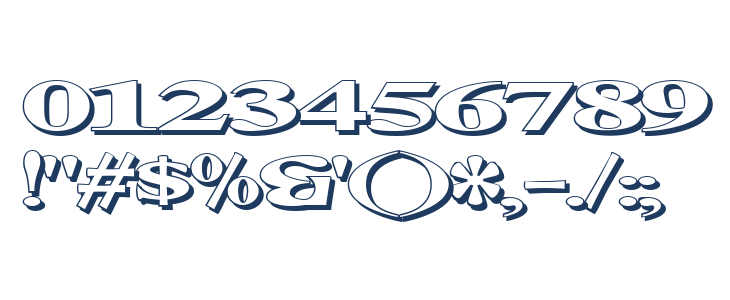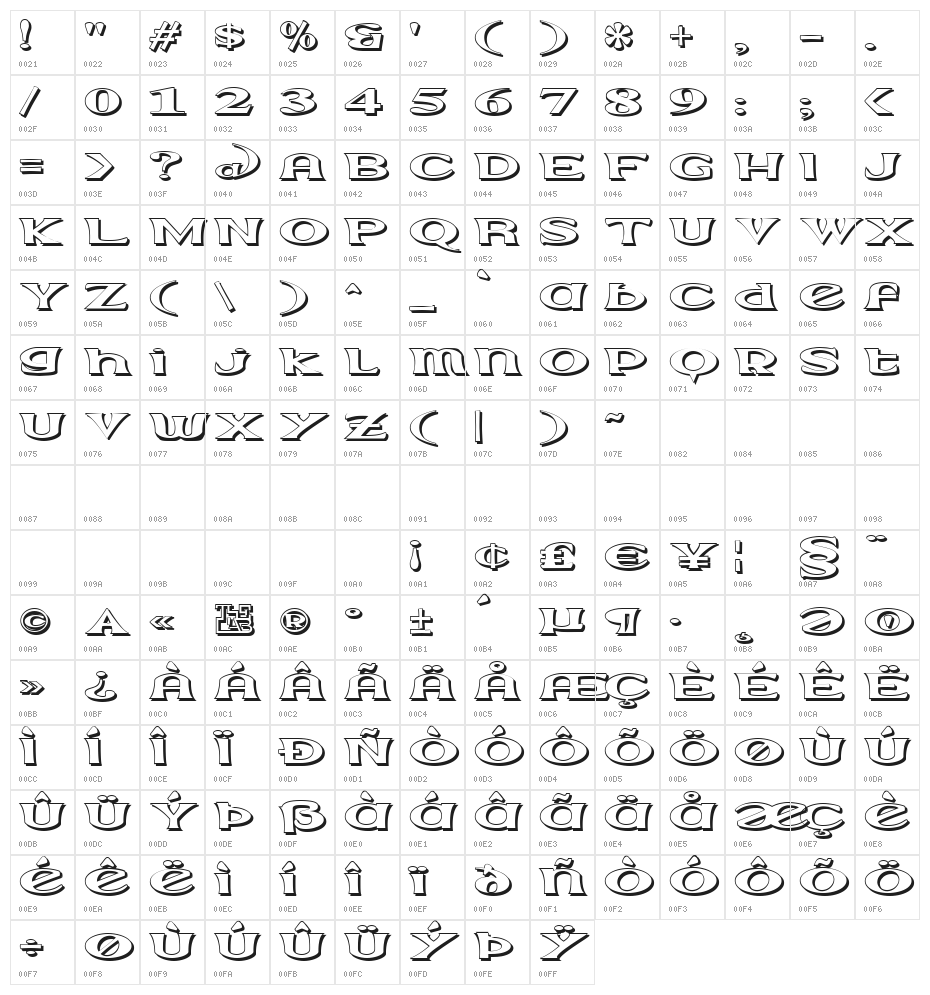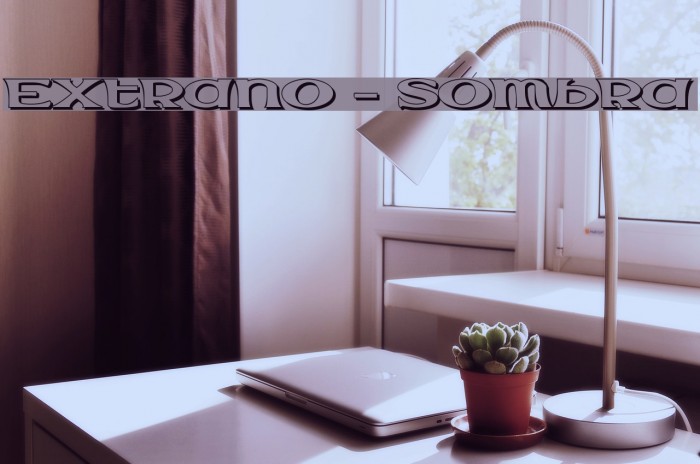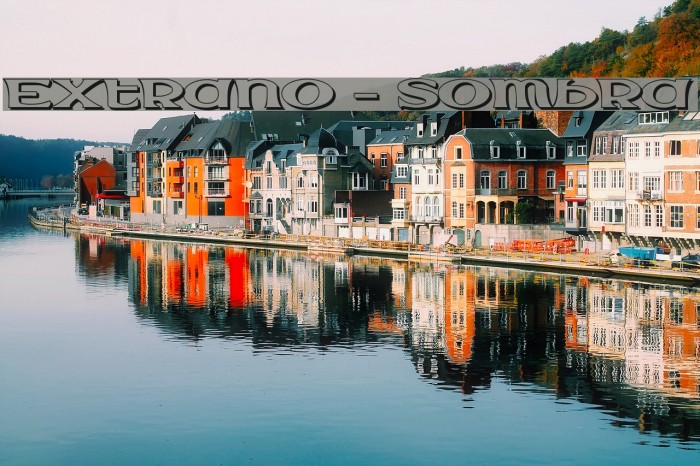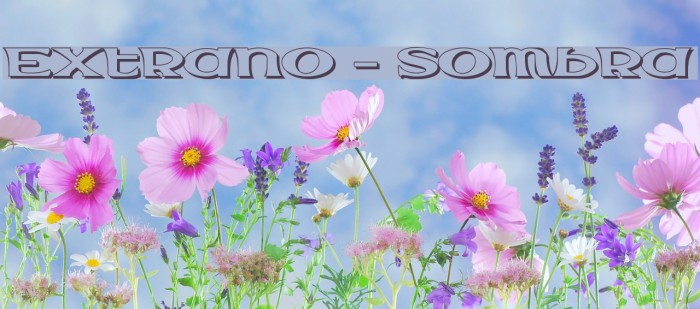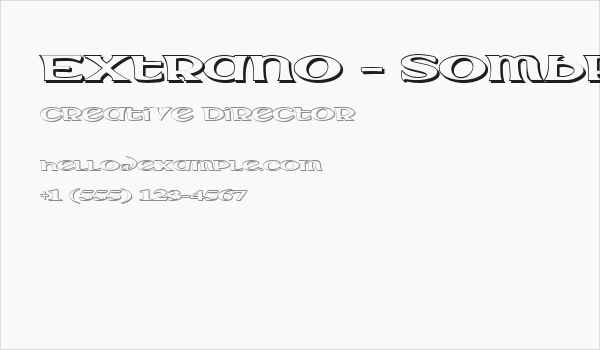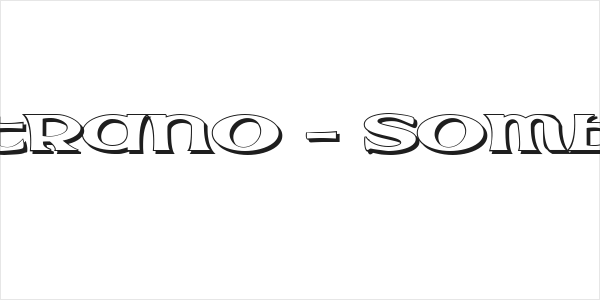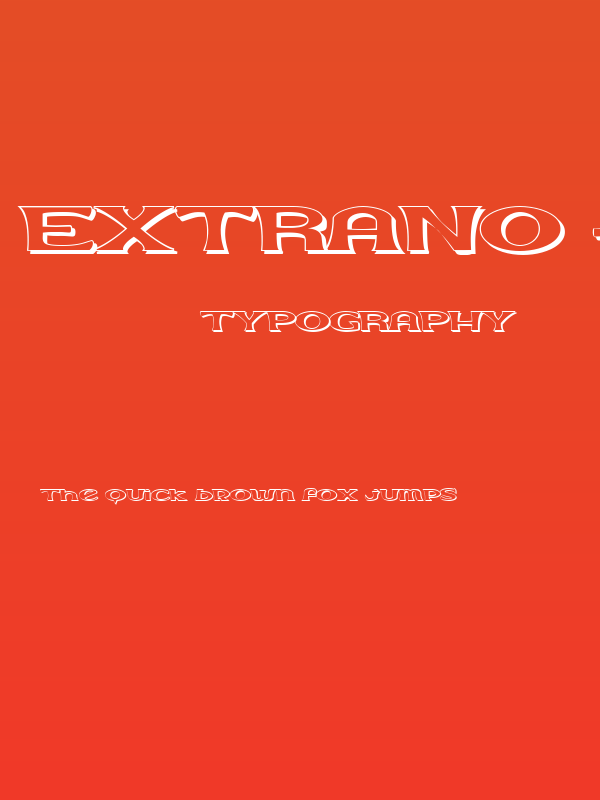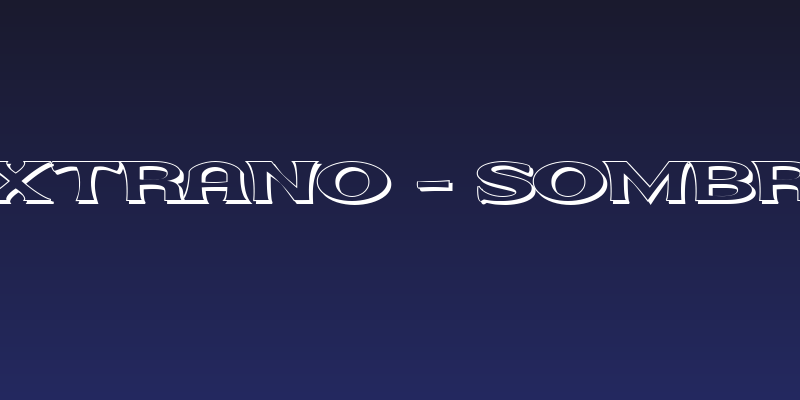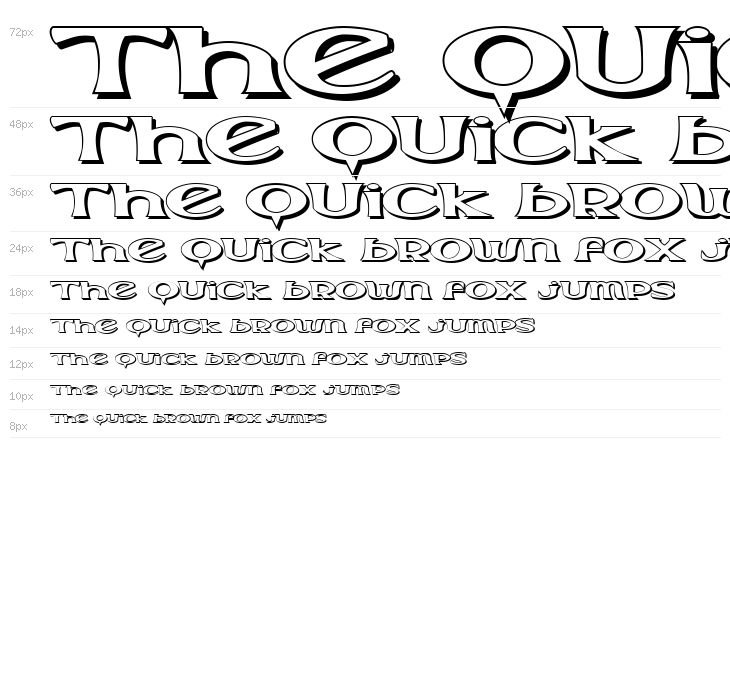
Extrano - Sombra Font
| Progetti proposti | This font is perfect for poster designs, branding projects, and any creative work that requires a bold statement. Its unique style can enhance logos, headlines, and promotional materials. |